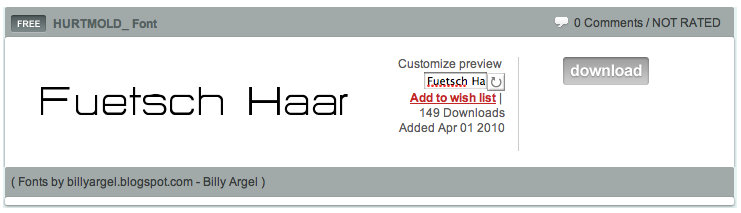
2 Schriften gesucht, Daten gingen verloren
ich suche 2 verschiedene Schriftarten. Die Druckdaten sind futsch, und ich habe nur noch die gedruckten Visitenkarten, finde aber die Schrift nicht im Netz :-(
Könnt ihr mir helfen?
Könnte es sein, dass das t und das r von einer anderen Schriftart stammt?
Hat jemand ne Ahnung wegen der zweiten Schriftart? Sieht aus wie Myriad Pro, aber das kleine a stimmt nicht...
… Hat jemand ne Ahnung wegen der zweiten Schriftart? …
Hast du kein größeres Beispiel?
Hm, erinnert mich ein bisschen an die Corpid von Luc de Groot. Vorallem wegen der Ziffern und der Minuskeln b, g (die hat auch ein offenes g, z.B. das a ist aber unterschiedlich). Dies vielleicht als Ausgangspunkt für die Suche.
Schau dir mal die FF Advert an, die ist recht ähnlich, soweit man das bei der Größe beurteilen kann.
Nachtrag: Die gibt es auch in Light.
Ich vermute einen Frutiger-Klon …
Die FF Advert Light sieht dem ganzen tatsächlich am ähnlichsten!